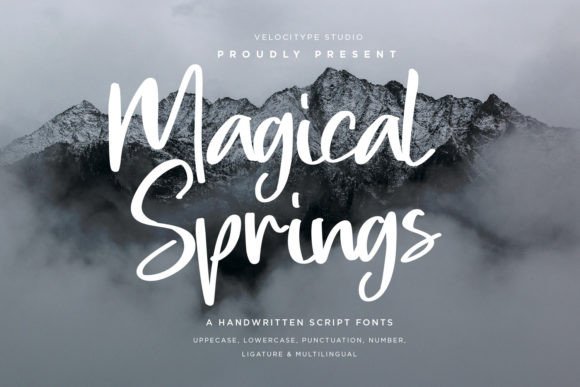
Magical Springs
Magical Springs์™€ ๊ฐ™์€ ๊ณ ํ’ˆ์งˆ ์ž์‚ฐ์„ ์ฐพ๊ณ  ์žˆ๋‹ค๋ฉด ์ด ํ”„๋ฆฌ๋ฏธ์—„ ํŒจํ‚ค์ง€๋Š” ์ฐฝ์˜์ ์ธ ํ”„๋กœ์ ํŠธ๋ฅผ ์œ„ํ•œ ํ™˜์ƒ์ ์ธ ์„ ํƒ์ž…๋‹ˆ๋‹ค.
์ •๋ฐ€ํ•˜๊ฒŒ ์ œ์ž‘๋œ Magical Springs๋Š” ๊น”๋”ํ•œ ๋ฒกํ„ฐ, ๋ถ€๋“œ๋Ÿฌ์šด ํƒ€์ดํฌ๊ทธ๋ž˜ํ”ผ ๋ฐ ์•ˆ์‹ฌํ•  ์ˆ˜ ์žˆ๋Š” ์ƒ์—…์šฉ ๋ผ์ด์„ ์Šค๋ฅผ ์ œ๊ณตํ•ฉ๋‹ˆ๋‹ค.
POD(์ฃผ๋ฌธํ˜• ์ธ์‡„) ์ œํ’ˆ, ๊ฒฐํ˜ผ์‹ ์ดˆ๋Œ€์žฅ ๋˜๋Š” ์†Œ์…œ ๋ฏธ๋””์–ด ๊ทธ๋ž˜ํ”ฝ์„ ๋งŒ๋“ค ๋•Œ Magical Springs๋Š” ์ด์ƒ์ ์ธ ์„ ํƒ์ž…๋‹ˆ๋‹ค.